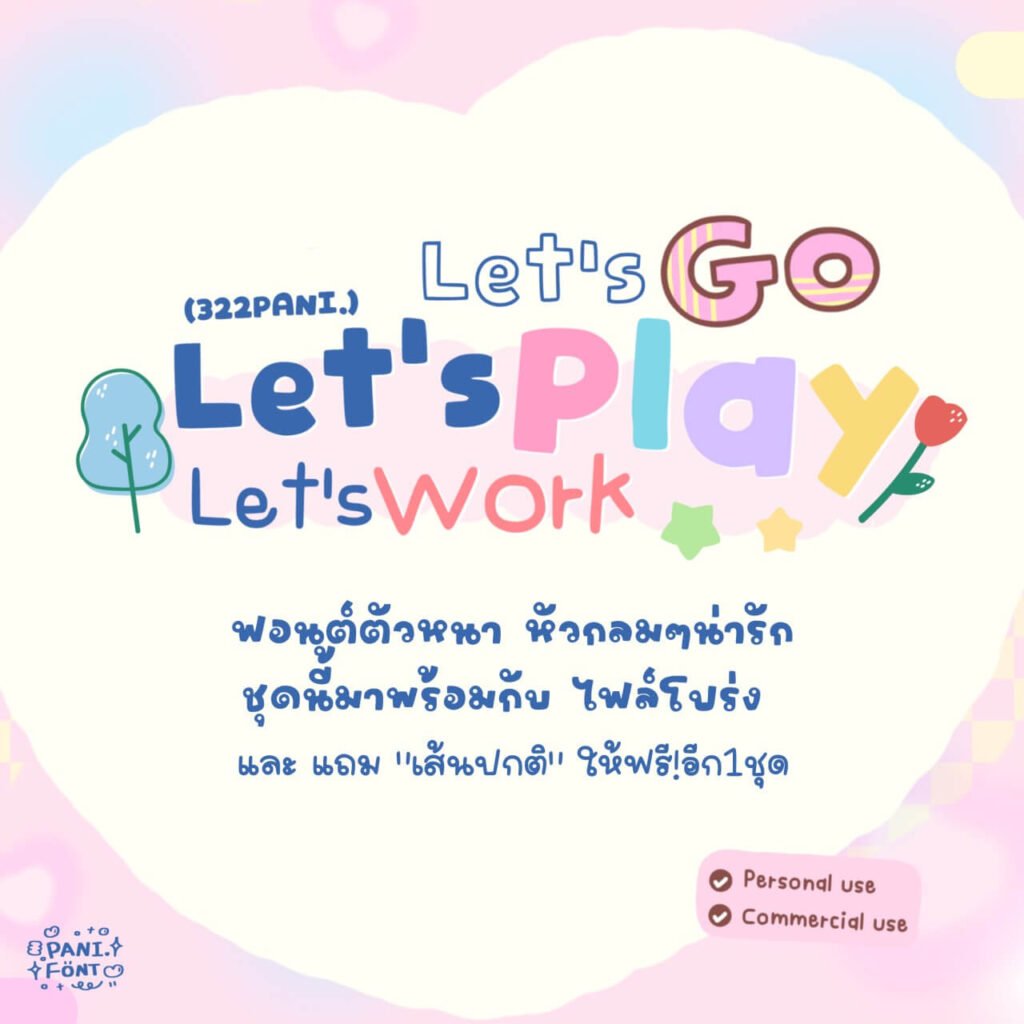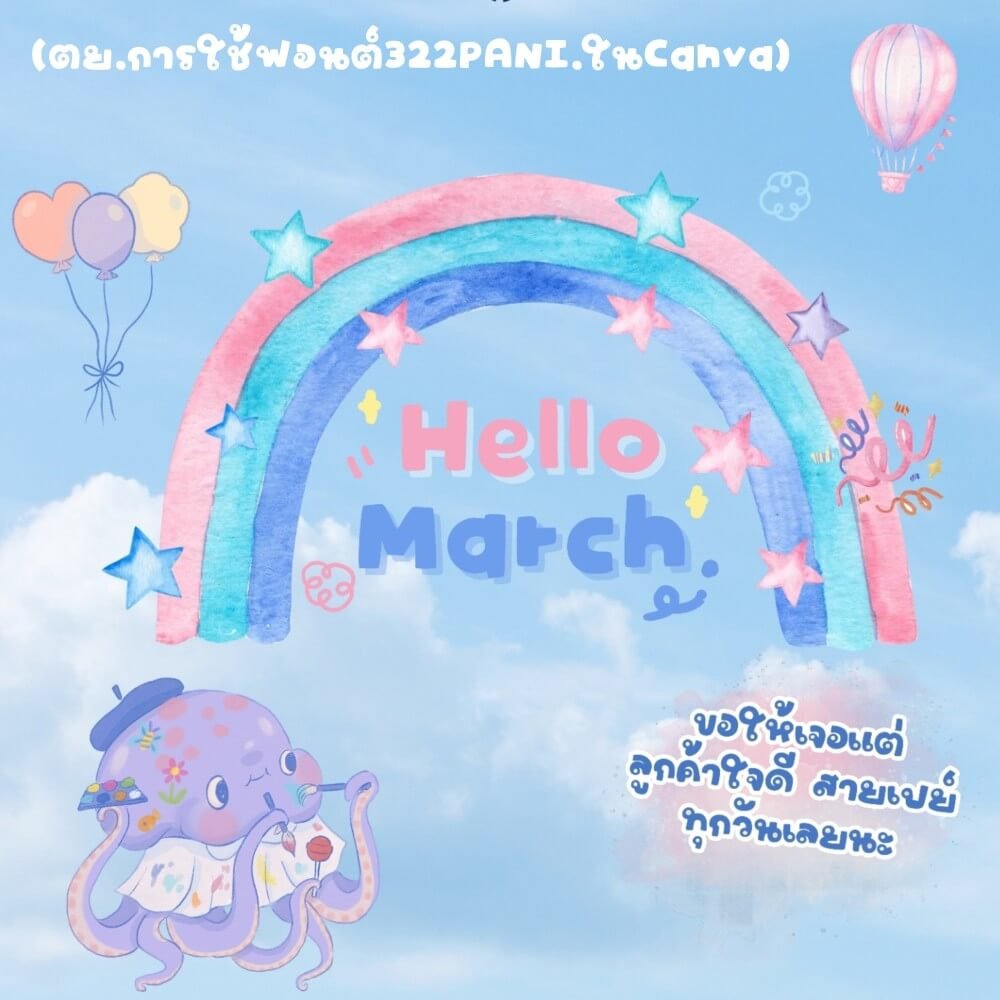
322PANI.Let’sPlay
ฟอนต์ 322PANI.Let’sPlay โหลดใช้ฟรีตัว Demo – ฟอนต์ตัวหนา หัวกลมๆ น่ารัก ชุดนี้แอนทำแบบครบเครื่องเลยค่ะ 7 ไฟล์ เรียกได้ว่า คุ้มสุดๆ นานๆ จะทำครบๆ สักที ไม่ควรพลาด ทั้งสายตั้งเป็นฟอนต์เครื่อง/ทำคลิป/คอนเทนต์ต่างๆ คือจุกๆ ใจ
*ชุดนี้มีไฟล์โปร่ง ไว้ลงสีเองด้วยนะคะ จะลงสีแบบสายคมเข้ม หรือพลาสเทลก็สวย
ฟอนต์มี 3 สไตล์ 7 ไฟล์ – น้ำหนัก บาง ปกติ หนา